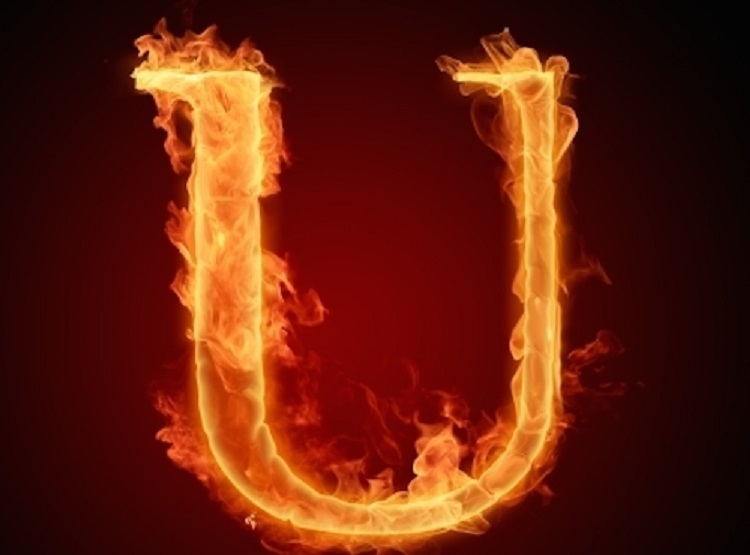
Tuyển tập 100+ chữ U kí tự đặc biệt ưa chuộng, in hoa, viết thường, viết ngược và kết hợp đẹp
Chữ U kí tự đặc biệt là các biến thể sáng tạo hoặc nghệ thuật của chữ cái U thông thường, được mã hóa bằng Unicode hoặc tổ hợp ký hiệu để tạo hiệu ứng lạ mắt. Loại kí tự này được ứng dụng rộng rãi trong thiết kế, ngôn ngữ lập trình, văn bản nghệ thuật hay tên tài khoản mạng xã hội.
Trong bài viết dưới đây, MobiFonts đem đến cho bạn tuyển tập 100+ kí tự đặc biệt chữ U chia theo 5 nhóm: ưa chuộng, in hoa, in thường, viết ngược và kết hợp đẹp, giúp bạn tạo dấu ấn riêng. Ngoài ra, chúng tôi còn giải đáp 4 câu hỏi thường gặp nhất để bạn có thể ứng dụng chúng một cách hiệu quả.
Chữ U kí tự đặc biệt là những phiên bản cách điệu, biến thể hoặc được mã hóa bằng Unicode của chữ U thông thường. Đây là kí tự được nhiều người ưa chuộng để tạo điểm nhấn khi đặt tên nhân vật trong game, trên mạng xã hội hay thiết kế nội dung sáng tạo. Dưới đây là một số kiểu chữ U phổ biến dành cho bạn, bao gồm: biểu tượng, tên Unicode, mã Unicode và mô tả ngắn.
Biểu tượng |
Tên Unicode |
Mã Unicode |
Mô tả ngắn |
Ũ |
Latin Capital Letter U with Tilde |
U+0168 |
Chữ U hoa có dấu ngã |
Ū |
Latin Capital Letter U with Macron |
U+016A |
Chữ U hoa có dấu ngang (macron) |
Ʉ |
Latin Capital Letter U Bar |
U+0244 |
Chữ U hoa có gạch giữa |
Ǔ |
Latin Capital Letter U with Caron |
U+01D3 |
Chữ U hoa có dấu mũ ngược |
ᴜ |
Latin Small Letter U (Modifier) |
U+1D1C |
Chữ u thường kiểu phiên âm |
ʊ |
Latin Small Letter Upsilon |
U+028A |
Biến thể u trong ngữ âm học |
ᵾ |
Latin Small Letter U Bar |
U+1D7E |
Chữ u thường có gạch giữa |
Ṳ |
Latin Capital Letter U with Diaeresis Below |
U+1E72 |
Chữ U hoa có dấu hai chấm dưới |
ʋ |
Latin Small Letter V with Hook |
U+028B |
Biến thể của v dùng trong phiên âm |
Ụ |
Latin Capital Letter U with Dot Below |
U+1EE4 |
Chữ U hoa có dấu chấm dưới |
Để tạo phong cách riêng biệt trong tên hiển thị, tin nhắn hay bài đăng của mình, bạn có thể tham khảo những kí tự đặc biệt chữ U in hoa. Dưới đây là một số chữ kiểu U in hoa đặc biệt mà bạn có thể lựa chọn:
Biểu tượng |
Tên Unicode |
Mã Unicode |
Mô tả ngắn |
𝐔 |
Mathematical Bold Capital U |
U+1D418 |
Chữ U hoa kiểu in đậm toán học |
𝕌 |
Double-Struck Capital U |
U+1D514 |
Chữ U hoa kiểu nét đôi |
𝒰 |
Mathematical Script Capital U |
U+1D4B0 |
Chữ U hoa kiểu viết tay nghiêng |
𝓤 |
Mathematical Bold Script Capital U |
U+1D4E4 |
Chữ U hoa kiểu viết tay đậm |
𝔘 |
Mathematical Fraktur Capital U |
U+1D518 |
Chữ U hoa kiểu chữ Fraktur (Đức cổ) |
𝘜 |
Mathematical Sans-Serif Italic Capital U |
U+1D658 |
Chữ U hoa không chân nghiêng (toán học) |
🅄 |
Squared Latin Capital Letter U |
U+1F144 |
Chữ U trong khung vuông |
🅤 |
Negative Squared Latin Capital Letter U |
U+1F164 |
Chữ U trong khung vuông nền đen |
Ⓤ |
Circled Latin Capital Letter U |
U+24CA |
Chữ U hoa trong vòng tròn |
𝗨 |
Mathematical Sans-Serif Bold Capital U |
U+1D5B0 |
Chữ U hoa không chân đậm (toán học) |
Nếu đang tìm kiếm các kiểu chữ U kí tự đặc biệt viết thường với phong cách đặc biệt để tạo điểm nhấn cho tên hiển thị, bài đăng hoặc tin nhắn, hãy tham khảo ngay các gợi ý dưới đây.
Biểu tượng |
Tên Unicode |
Mã Unicode |
Mô tả ngắn |
𝑢 |
Mathematical Italic Small u |
U+1D462 |
Chữ u thường nghiêng kiểu toán học |
𝒖 |
Mathematical Bold Italic Small u |
U+1D4D6 |
Chữ u thường đậm nghiêng kiểu toán học |
𝖚 |
Mathematical Double-Struck Small u |
U+1D5DA |
Chữ u thường kiểu Fraktur (phong cách cổ điển) |
𝐮 |
Mathematical Bold Small u |
U+1D42E |
Chữ u thường đậm kiểu toán học |
𝘶 |
Mathematical Sans-Serif Italic Small u |
U+1D68A |
Chữ u thường không chân nghiêng toán học |
ⓤ |
Circled Latin Small Letter u |
U+24E4 |
Chữ u thường trong vòng tròn |
𝗎 |
Mathematical Sans-Serif Small u |
U+1D68C |
Chữ u thường không chân kiểu toán học |
𝔲 |
Mathematical Fraktur Small u |
U+1D532 |
Chữ u thường kiểu Fraktur (Đức cổ) |
𝓊 |
Mathematical Script Small u |
U+1D4CA |
Chữ u thường viết tay kiểu toán học |
Chữ U kiểu viết ngược mang đến một hiệu ứng độc đáo, giúp nội dung trông mới lạ hơn, thu hút sự chú ý của người xem. Đây là lựa chọn hoàn hảo để tạo điểm nhấn trong tên hiển thị, bình luận hoặc bài đăng trên mạng xã hội. Một số kiểu chữ U ngược phổ biến bao gồm:
∩
∩̿̿
∩͜͡
∩҉
n͢
n̳
n̲
𝚗̷
n̷
Chữ U kí tự đặc biệt kết hợp với các biểu tượng khác giúp tạo nên phong cách riêng biệt. Tham khảo các kí tự chữ U kết hợp dưới đây: